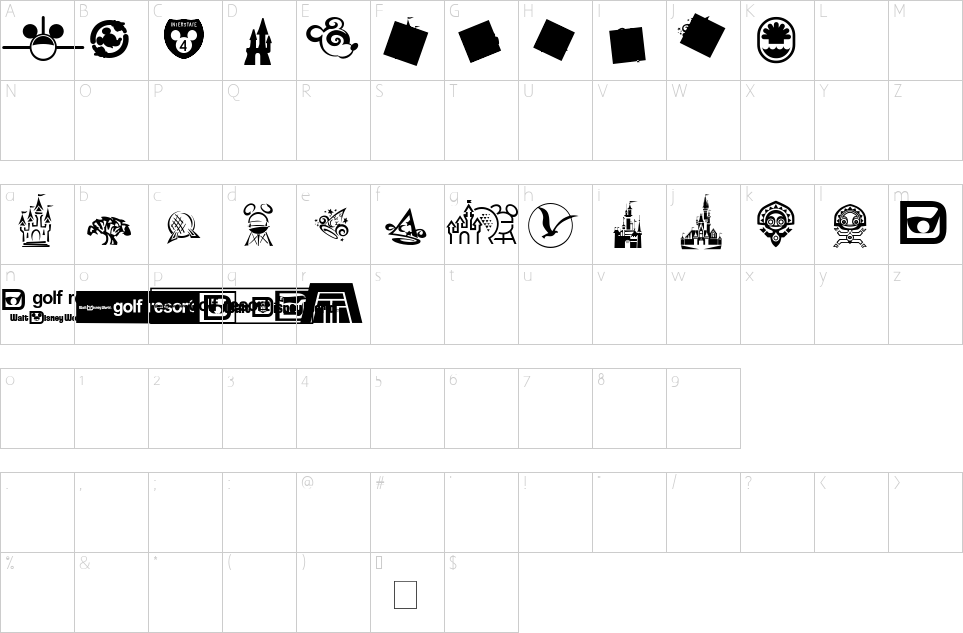
Descubra a elegância e a versatilidade da Mouse Tags font, uma elegante e sofisticada seleção de caracteres que adicionará um toque único a seu design. Com seu designer não revelado, Steve Ferrera, a Mouse Tags font foi projetada com atenção aos detalhes, oferecendo uma ampla gama de opções para textos em Windows e Mac. Esta fonte está disponível gratuitamente para download, já tendo sido baixada 118,522 vezes. Adquira a Mouse Tags font e adicione sofistica e modernidade ao seu próximo projeto. Seja para contratos, sites ou qualquer outro tipo de material gráfico digital, a Mouse Tags font é a escolha ideal para quem busca uma fonte profissional e moderna para seus trabalhos.